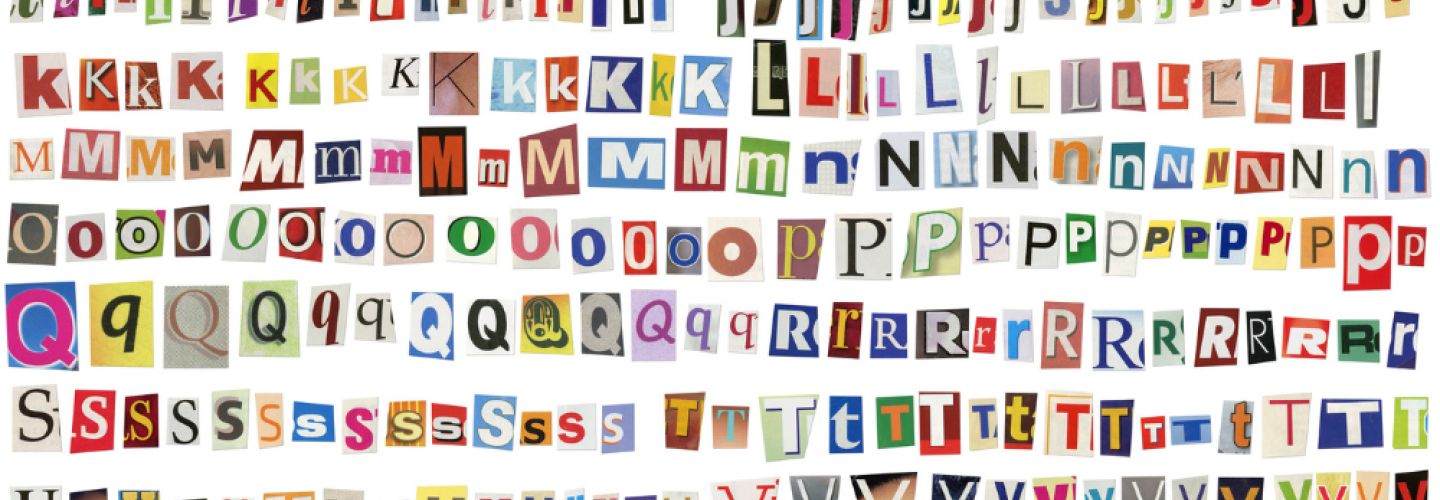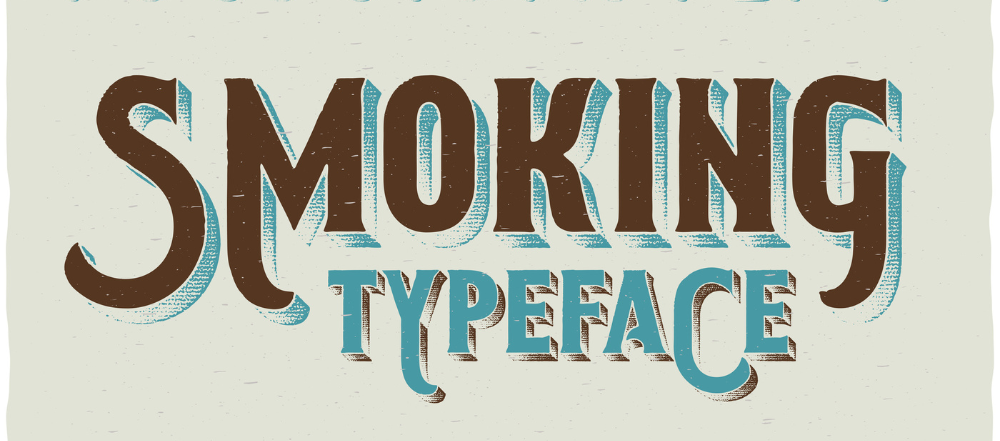
¿Qué es la tipografía y qué psicología hay detrás de ella?
Seguro que has visto alguna vez la tipografía, que es un elemento fundamental dentro del diseño gráfico, de producto y editorial. No olvides que, con la tipografía, puedes transmitir un sinfín de mensajes, algo que es muy importante cuando hablamos de cualquier tipo de diseño.
¿Qué es la tipografía?
Bien, vamos a empezar por el principio. Al hablar de la tipografía, qué es, hay que comenzar por los cimientos. De una forma muy básica podemos definirla como el arte de colocar letras y texto para que este genere un mensaje claro, atractivo y perfectamente legible.
Esto incluye, naturalmente, el estilo, la estructura y la apariencia de las fuentes usadas, que persiguen el objetivo de generar emociones y transmitir mensajes.
Sus orígenes datan del siglo XI, cuando se produjo la modificación de los tipos móviles. Antes de la revolución digital, la tipografía se asociaba al sector editorial, específicamente.
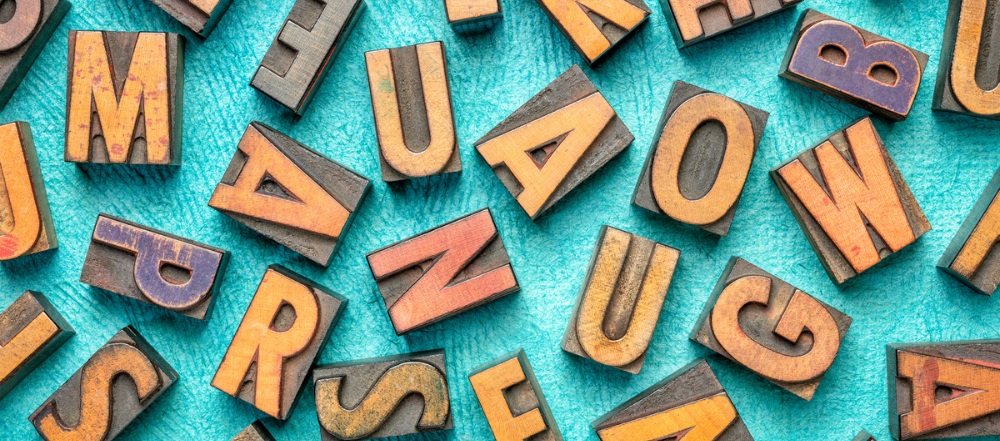
El ejemplo claro primigenio de tipografía y qué es lo encontramos en la Biblia de Gutenberg, el responsable de la revolución occidental en este sentido. Como dato anecdótico, te diremos que la fuente que se usó en este documento hoy se llama Textura, y está disponible para su utilización.
Sin embargo, hoy las cosas son muy diferentes y la tipografía se vincula más al mundo digital y a la impresión. Hemos asistido a la versión más creativa con la llegada de internet: de repente, los profesionales del diseño tienen una ingente cantidad de opciones a su disposición.
La clasificación tipográfica según su significado
Como hemos dicho al hablar de la tipografía, que es fundamental para transmitir un mensaje, cada tipo de fuente tiene un significado, y eso es lo que vamos a ver a continuación.
Tipos rounded
Estas son las más redondeadas, como pueden ser el tipo Comfortaa, o la Helvética Neue. Sus formas más suaves transmiten una sensación de cercanía, lo que las hace adecuadas para proyectos menos formales.
Fuentes condensadas
Un ejemplo de estas tipos es la fuente Oswald. Una de sus características es que, como son un poco más estrechas de lo normal, pueden ser un poco más duras, pero lo cierto es que tienen una personalidad única.
Precisamente este es su significado: la personalidad y la formalidad.
Serif
La fuente tipo serif es algo que en la tipografía es muy popular. Estas son las que no tienen un acabado recto o redondo. Un ejemplo es la Playfair Display, y transmiten una gran personalidad. La elegancia es un aspecto que emiten, y el contraste en sus trazos las hacen únicas.
Para proyectos más serios y formales son perfectas.
Modernas
Las llamadas fuentes modernas, como la Montserrat, son fácilmente usadles para cualquier entorno. Son neutras, y encajan en casi cualquier proyecto.
Tipografías script
Estos tipos, como la Parisienne, tienen las letras ligadas. Transmiten elegancia, calidad y lujo. Son perfectas para proyectos que pretendan dar la impresión de ser elaborados con un toque clásico.
Psicología detrás de la tipografía
Se dice que tras la tipografía hay psicología, puesto provoca una reacción emocional y visual. En este sentido, y en función de lo que veamos, nuestro pensamiento, los sentimientos y las acciones se verán afectados de forma distinta.
Por ejemplo, si alguien ve una marca de fitness que trata de ganar fuerza utilizando una fuente en negrita, su clientela verá dicha fuente y pensarán: grueso, voluminoso y pesado. Esta percepción se asociará también a la marca de fitness.
Forma y color
En la psicología de la forma, hay que fijarse en la geometría y en qué provoca en los espectadores y espectadoras. Esto también afecta a las fuentes, ya que tienen elementos de formas geométricas. Un tipo de letra podría ser más redondeada para crear relajación o tranquilidad, o con líneas rígidas, trasladando una sensación diferente. La psicología del color también desempeña un enorme papel en el cambio del estado de ánimo, fluctuando a través de diferentes matices y tonos.
Con ella puedes impulsar tus decisiones y objetivos. Así, si entiendes cómo reacciona la gente ante las fuentes, podrás influir en la forma en la que tu diseño y tu negocio son percibidos por las personas a las que te gustaría dirigirte.
¿Cómo saber qué tipografía usar?
A la hora de elegir la tipografía, que es algo muy importante, hay que tener en cuenta varios factores.
- Comprender la identidad. Ten en cuenta que comunicará un mensaje no verbal, y que el tipo que escojas debe ir con la marca.
- Analiza las marcas que conoces. Echa un vistazo a sus tipos y piensa en qué te transmiten.
- Coherencia. La fuente que elijas debe poder crear un paraguas para toda tu marca y su identidad corporativa.
- Elige algunas tipografías iniciales. Luego descarga tres de ellas, y compara.
- Considera siempre la jerarquía tipográfica. Si piensas usar varias tipografías, asegúrate de que funcionan bien.
Twitter: la fuente de esta red social es una modificación de la Pico Alphabet, y cuenta con extremos redondeados y trazos amables que muestran que las ideas pueden confluir de forma conjunta.
IBM: la tecnológica utiliza la fuente ITC Lubalin Graph para transmitir la gran energía de la marca.
Nike: La marca de ropa deportiva comparte su fuente con empresas como Cisco o Gilette. Hablamos de la Futura, aunque cada marca la adapta a sus necesidades.